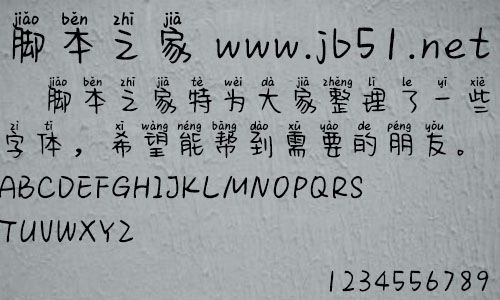
Aa芳心縱火犯一款不錯(cuò)的的藝術(shù)字體,由Aa字庫(kù)出品,字體筆觸適中,字形圓潤(rùn),適合應(yīng)用于藝術(shù)設(shè)計(jì)、平面宣傳設(shè)計(jì)、網(wǎng)頁(yè)設(shè)計(jì),書法字帖等領(lǐng)域,需要的朋友可以前來本站下載。